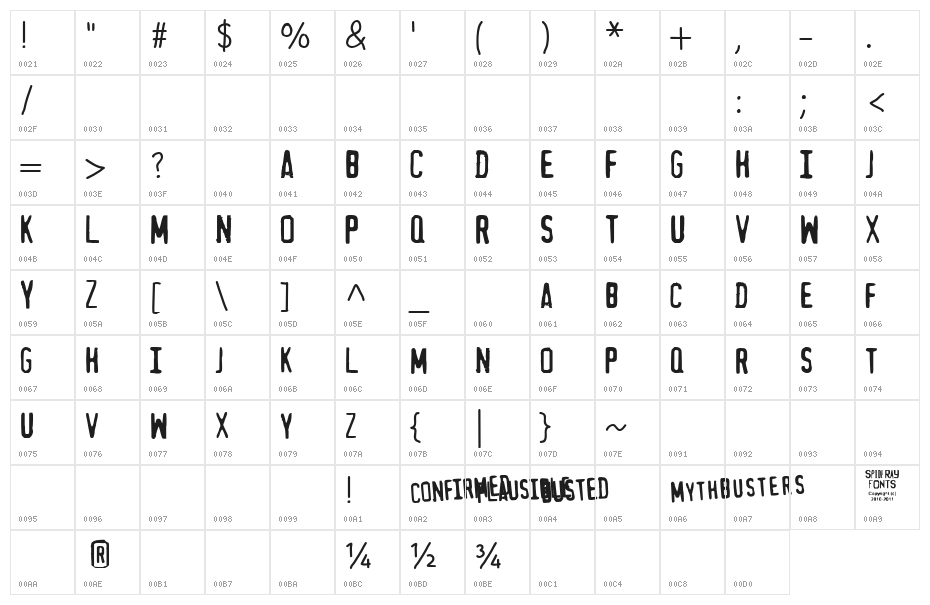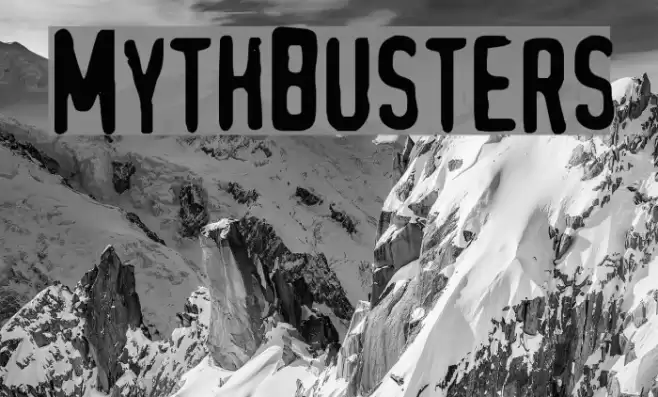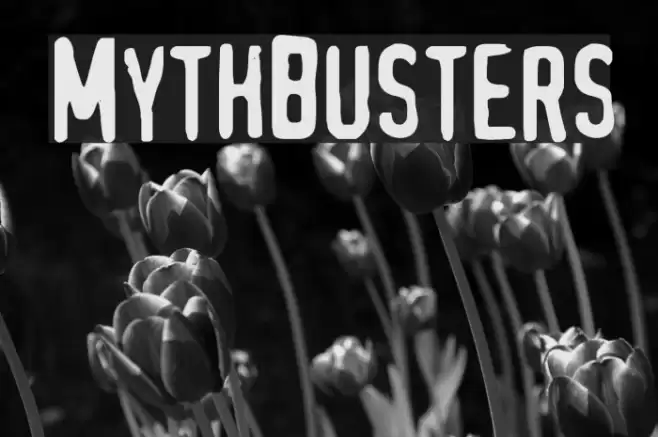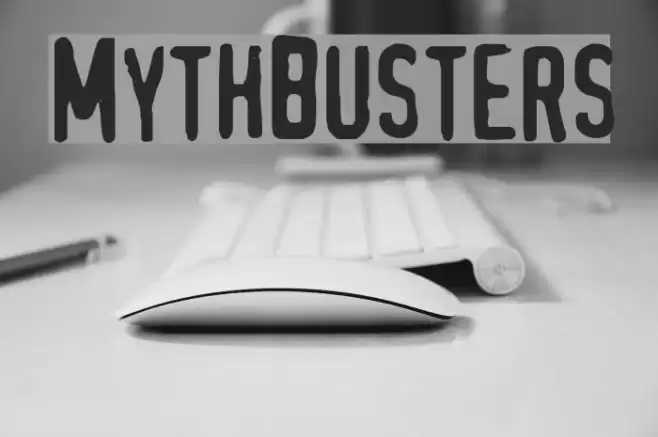
MythBusters Font
✎ Distorted Eroded
| カテゴリ | Distorted Eroded |
| 全体的なスタイル | Vintage, Industrial |
| おすすめプロジェクト | Ideal for branding, posters, and packaging designs that require a vintage or industrial aesthetic. Suitable for creating logos, headlines, and promotional materials that need a bold, eye-catching look. |